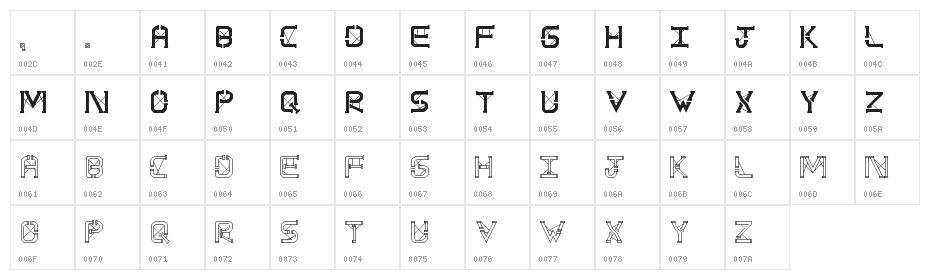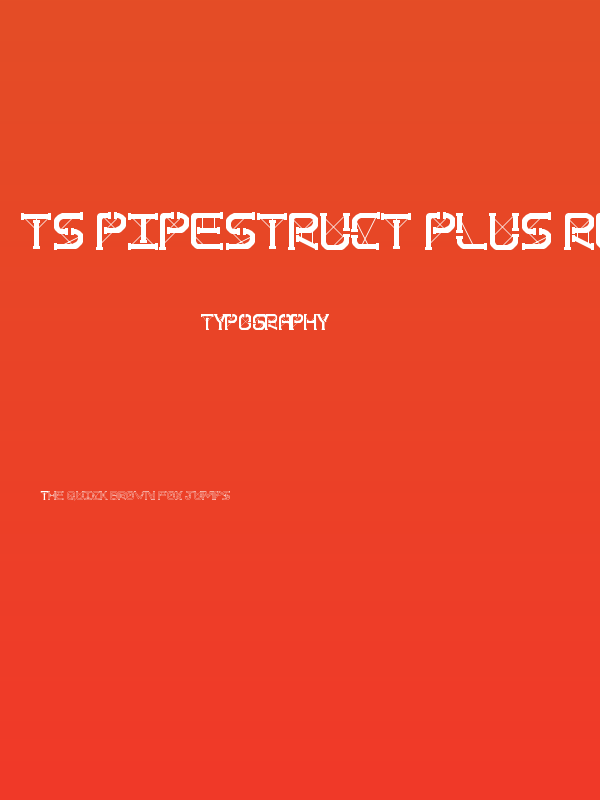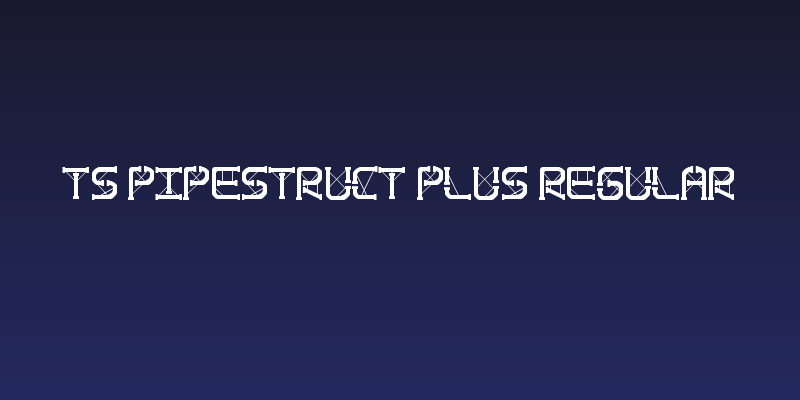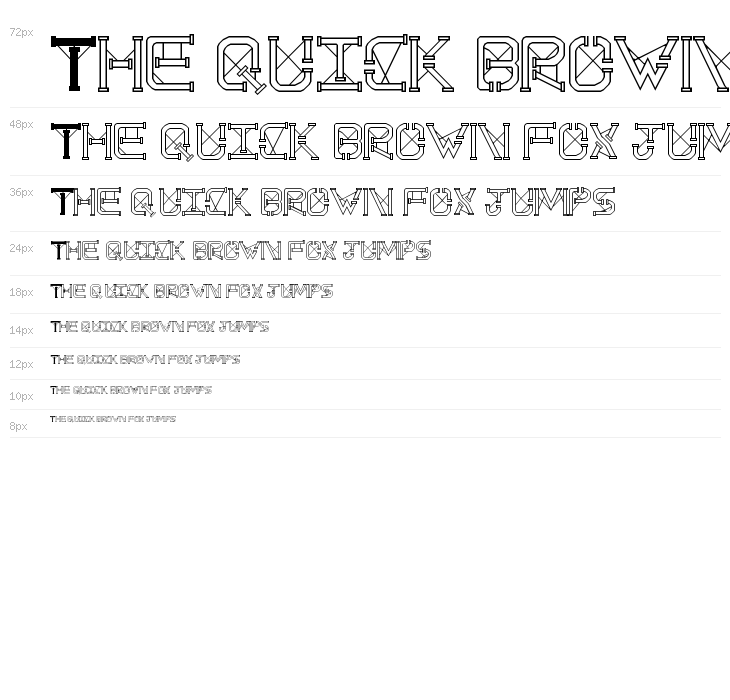
TS PipeStruct Plus Regular Font
| Estilo general | Modern, Industrial |
| Caso de uso | Logos, Posters, Branding |
| Proyectos propuestos | Ideal for branding, logos, posters, and any design project that requires a modern, industrial touch. |